Расставляем акценты: шрифты для ярких заголовков
Мы много говорим об универсальных «рабочих лошадках». Такие шрифты популярны, их характер чаще нейтрален, а кассовый состав — обширен. Один такой шрифт, например, TT Norms® Pro, может использоваться в тысяче проектов с разной тематикой и выглядеть уникально в каждом.
Универсальные шрифты очень востребованы. Но чем расставлять акценты? Можно использовать и «рабочие лошадки», но, когда нужно передать сильную эмоцию, лучше поискать вариант с более выразительным характером.
Сегодня речь пойдёт о них: изящных и дерзких, дружелюбных и брутальных, динамичных и устойчивых. Это — шрифты для акциденции. Они бывают разными по характеру и уровню выразительности, но всегда привлекают внимание читателя при правильном использовании.
Какими бывают шрифты для акциденции
Декоративных шрифтов не бывает много. Коллекция таких шрифтов у опытного дизайнера может превышать 400 гарнитур, и это далеко не предел. Потребность активнее пополнять коллекцию акцидентных шрифтов связана с тем, что подбирать их нужно более тщательно.
Декоративный шрифт должен подходить проекту безупречно, ведь именно в заголовках, логотипе и других крупных надписях заложены эмоциональные посылы, которые считывает аудитория.
Это шрифты, которыми привлекают внимание. Даже начинающий дизайнер понимает, что большой массив текста и заголовок не стоит набирать одним шрифтом и кеглем. В тексте важны акценты. От того, как их расставит дизайнер, зависит заинтересованность читателя.
Задача шрифта для набора текста — не отвлекать внимание от чтения, а акцидентного шрифта — привлекать. Чтобы зритель дошёл до массива текста, заголовок и другие акценты должны задержать внимание и вызвать желание прочитать статью, открыть книгу или совершить другое действие.
Хоть шрифты для акциденции — широкая группа, объединяющая множество стилей и видов, вы легко отличите их от других. Такие шрифты хочется разглядывать и изучать каждый штрих буквы, особенно когда текст набран в крупном размере.
В этой статье мы поговорим о трёх категориях шрифтов: об акцидентных, дисплейных и декорированных.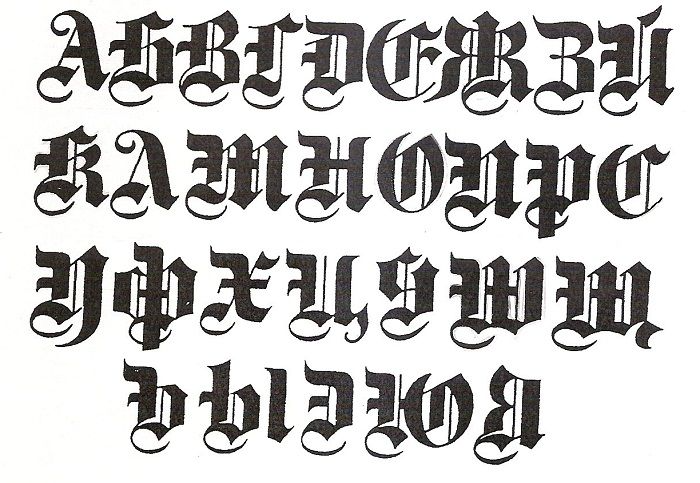
Акцидентные шрифты
На эту статью нас вдохновил TT Cometus, который вышел на площадки в январе 2023 года. Это стильный и выразительный шрифт с запоминающимся характером.
TT Cometus — идеальный пример акцидентного, или декоративного, шрифта. Его сложно представить в текстовом массиве, однако он гармонично смотрится в заголовках и крупных надписях.
Акцидентные шрифты — обширная категория. Сюда можно отнести все шрифты, которые предназначены для расстановки акцентов и не используются в текстовом наборе.
Сюда могут входить:
- рукописные шрифты;
- трафаретные шрифты;
- заголовочные шрифты;
- шрифты с орнаментом или с паттернами.
Акцидентные шрифты иногда называют декоративными. Они используются в наборе заголовков и логотипов, ими оформляют небольшие фразы или цитаты в массиве текста. Уровень выразительности декоративных шрифтов бывает разный. Чем слабее выражен характер шрифта, тем более длинной может быть напечатанная шрифтом фраза.
Например, TT Cometus — шрифт с ярко выраженным характером. Лучше всего он выглядит в небольшом фрагменте текста, набранного крупным кеглем.
При этом шрифт сочетает в себе несколько стилей. В нём есть отсылки к каллиграфии, мощные засечки, характерные для брусковых шрифтов, а также плавность и пластичность форм, придающие характеру дружелюбность. Такое сочетание характерно для многих акцидентных шрифтов. Чтобы получить нужную степень выразительности и сделать характер уникальным, дизайнеры могут использовать разные приёмы и стили. В акцидентных шрифтах есть место творческой идее автора.
Такие шрифты часто бывают авторским проектом одного дизайнера. Чтобы передать эмоцию через шрифт, важно найти вдохновение при работе. При желании, отсылки к образам можно увидеть в названии самой гарнитуры.
«Название шрифта отсылает к образу кометы — мощного тела с красивым хвостом, несущегося с огромной скоростью»Акцидентные шрифты часто используются для логотипов и дизайна упаковки.
Иногда коммерческие шрифты кастомизируются, благодаря чему шрифт получается более уникальным.
Например, для бренда PetChoy мы кастомизировали узкий акцидентный гротеск TT Trailers. В некоторые из символов были добавлены силуэты кошек и собак. Это не только сделало шрифт более запоминающимся, но и добавило прямую отсылку к бренду, производящему корм для питомцев.
Про эту кастомизацию мы писали статью.
Кастомизированный TT Trailers для бренда PetChoyВ коллекцию акцидентных шрифтов TypeType входит много разных по характеру гарнитур.
Вы уже познакомились с яркими представителями: TT Cometus и TT Trailers.
Визуальная айдентика Theatre de la Croix Rousse.Представляем вашему вниманию другие стильные шрифты категории.
Тем, кто ищет акцидентный шрифт с простыми текстовыми формами, понравится TT Bluescreens. Его пропорции узкие, как и у TT Trailers, но характер позволяет использовать шрифт и в тексте, и в акциденции.